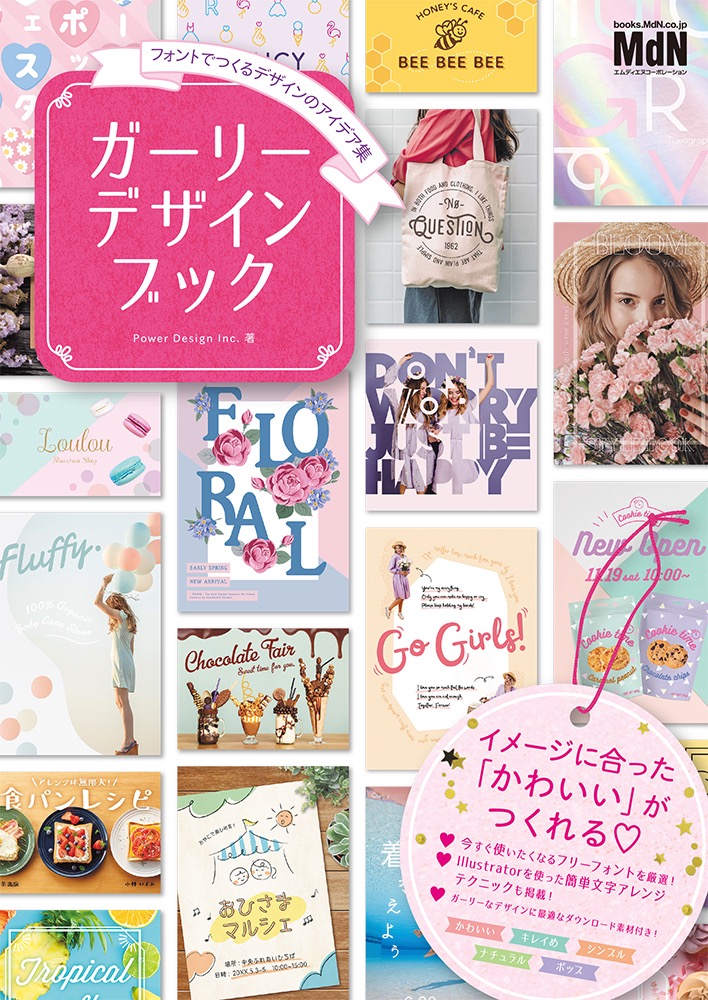
ガーリーデザインブック フォントでつくるデザインのアイデア集
インプレスグループでデザイン分野のメディア事業を手がけるエムディエヌコーポレーションは、Power Design Inc.著書による、イメージ通りのかわいいがつくれる「ガーリーデザインブック フォントでつくるデザインのアイデア集」を発売した。
「ガーリーデザインブック フォントでつくるデザインのアイデア集」は、フリーフォントを使ったデザイン作例やフォントのアレンジテクニックを紹介する、デザインのアイデア集。
Chapter1では、使い勝手のよい和文・欧文フリーフォントを使ったかわいいデザイン作例をたっぷり49点紹介。「かわいい」「キレイめ」「シンプル」「ナチュラル」「ポップ」の5つのカテゴリーに分かれているので、つくりたいイメージに最適なデザインを探すことができる。
Chapter2では、Illustratorでできる簡単な文字アレンジテクニックを15点掲載。デザインがどこか物足りないと感じるとき、このテクニックを使って一手間加えるだけで、簡単にオリジナル感がアップ。アレンジバリエーションも紹介しているので、デザインの幅が広がることまちがいなし。
Chapter3では、「ガーリーデザインブック フォントでつくるデザインのアイデア集」で紹介しているフリーフォントとアレンジテクニックを組み合わせてつくれるデザインサンプルを紹介しています。ポスターやポストカード、フライヤーなど、具体的なサンプルを掲載。サンプルの中で使っている素材は、ダウンロードして自由に使える。
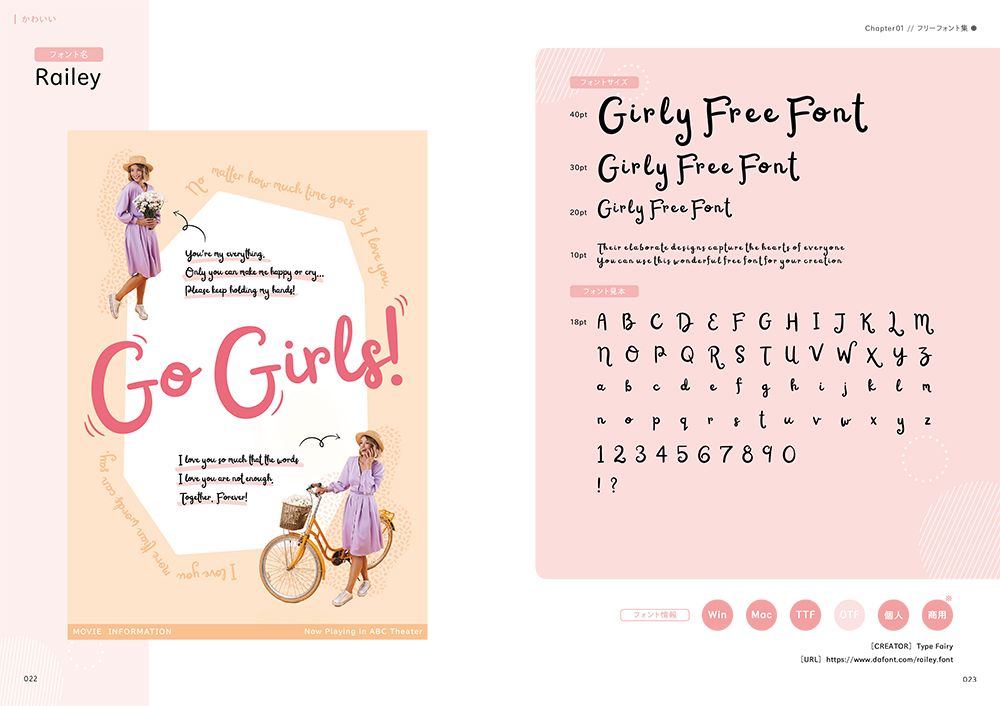
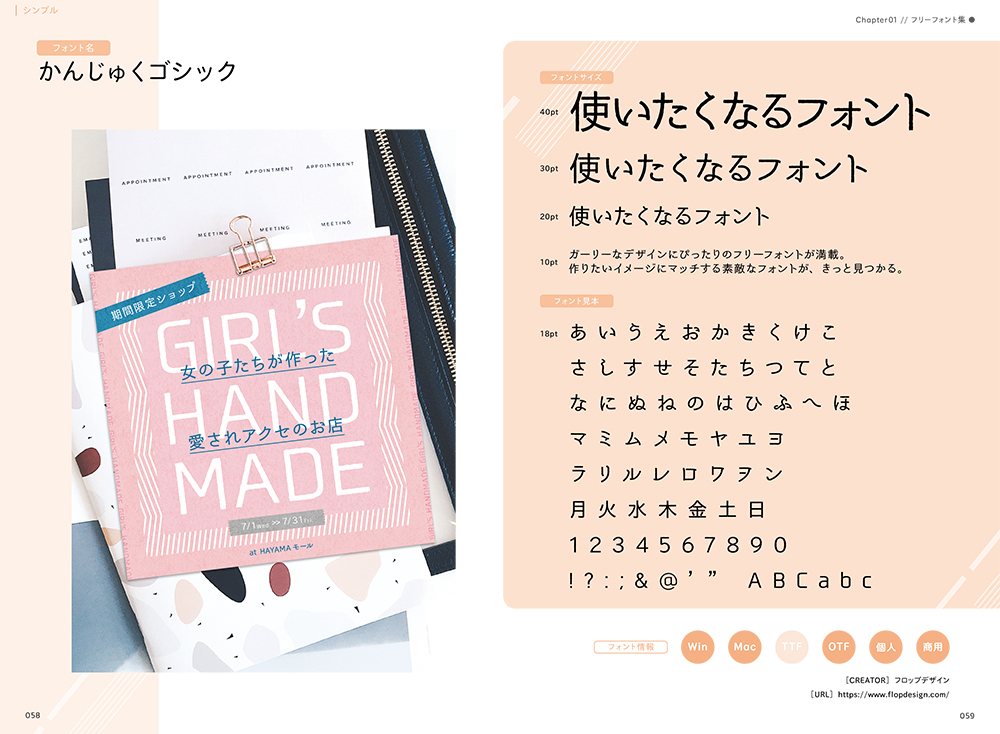
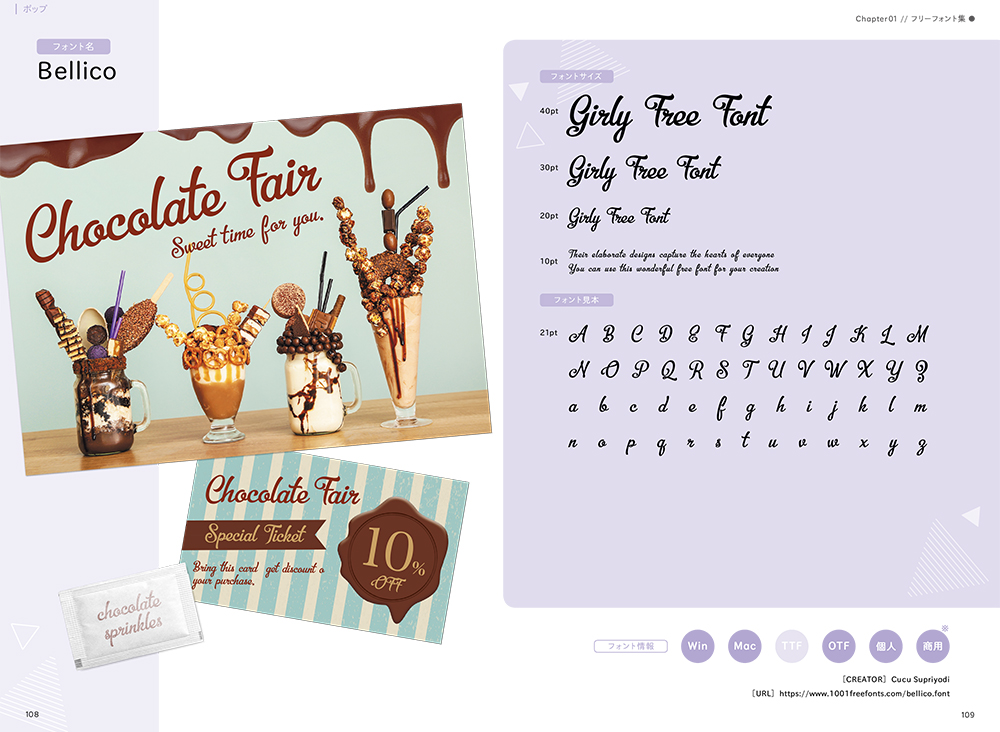
「ガーリーデザインブック フォントでつくるデザインのアイデア集」の主な内容
■Chapter1 フリーフォント集
カテゴリー別フォント紹介 かわいい/キレイめ/シンプル/ナチュラル/ポップ
■Chapter2 アレンジテクニック
1 かすれビンテージ
2 鉛筆スケッチ
3 フリーハンド
4 版ずれレトロ
5 上品シャドウ
6 ぷっくりツヤツヤ
7 映り込み
8 飛び出し ...ほか
■Chapter3 デザインサンプル
カテゴリー別デザインサンプル かわいい/キレイめ/シンプル/ナチュラル/ポップ